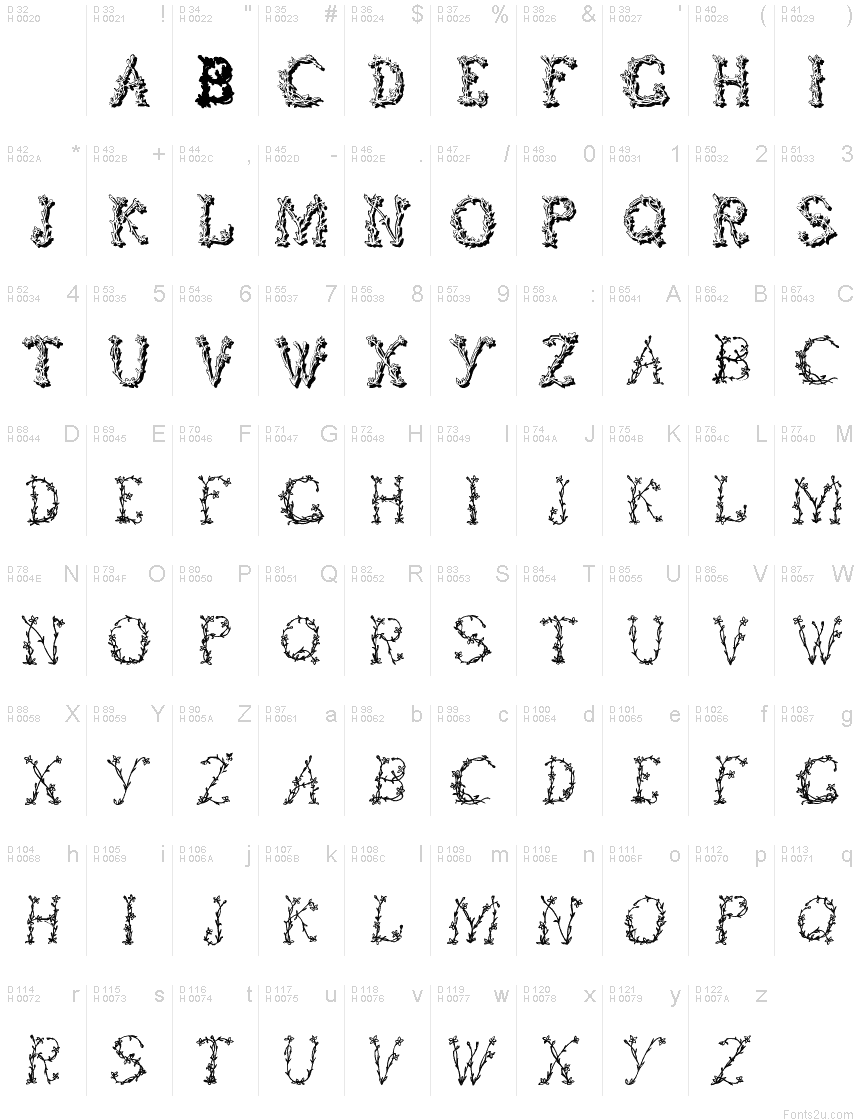
Floral Two di M. Klein è un carattere decorativo display gratuito che trasforma ogni lettera in un rampicante. Tratti sottili e inchiostrati si arricciano e si intrecciano formando steli, mentre piccoli fiori punteggiano le curve come un giardino disegnato a mano che cresce sulla pagina. La texture appare organica e leggermente selvaggia, conferendo ai titoli un fascino stravagante, da libro di fiabe, pur rimanendo chiaramente leggibile nei corpi grandi.
Con Floral Two, puoi dare una morbida impronta botanica a inviti di nozze, volantini per feste in giardino, branding ecologico, cartoline stagionali, packaging o post sui social a tema naturale. Questo font gratuito dà il meglio di sé se usato con parsimonia come marchio o titolo breve; abbinalo a un carattere sans serif pulito per il testo principale, per mantenere il layout arioso e leggibile.